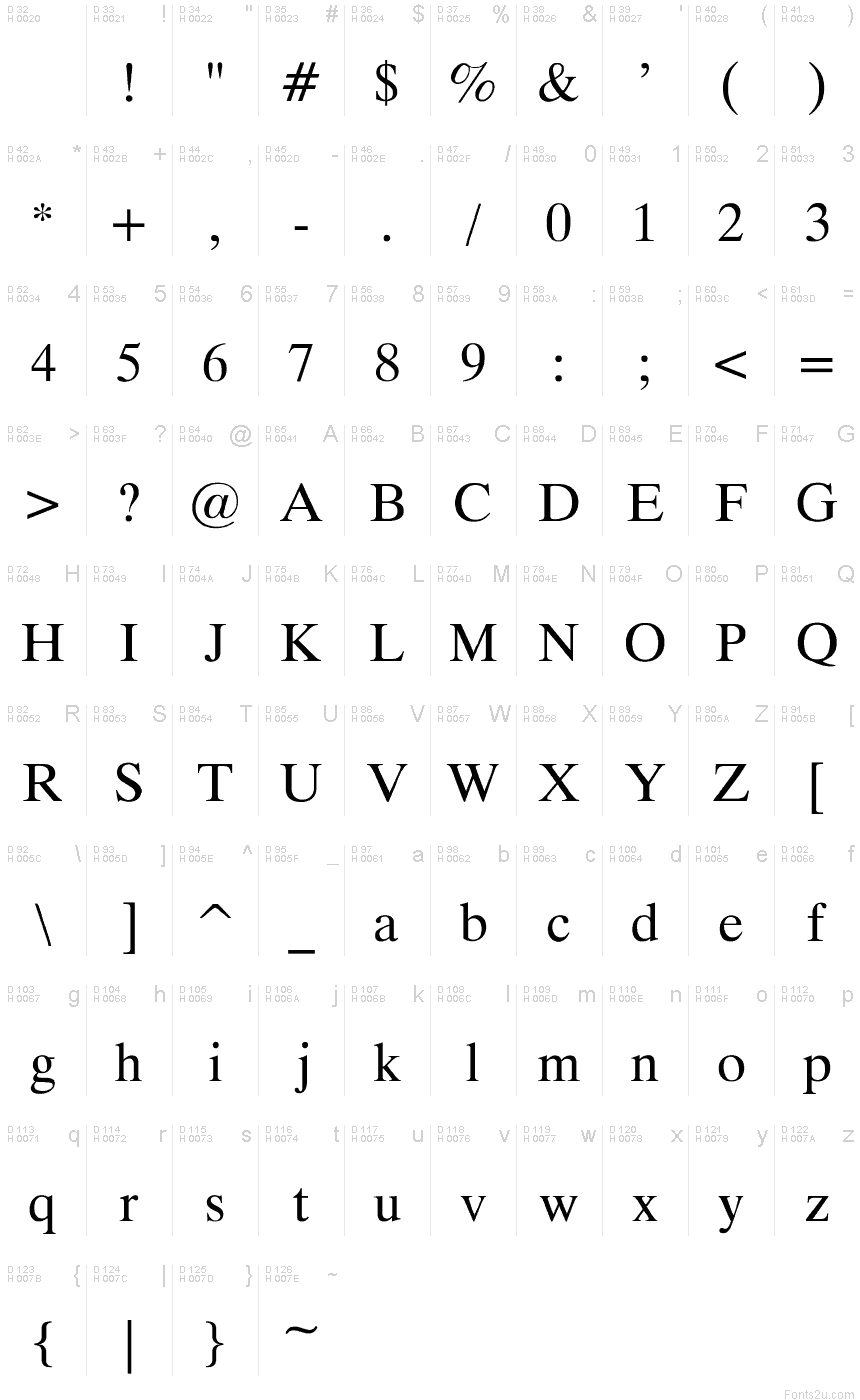
MicroTiempo od MicroCOM INC - Devoted to ShareWare to darmowy krój szeryfowy o wyważonym, książkowym charakterze typowym dla klasycznego druku. Jego rytm budują wysokie, lekko rozszerzające się kreski oraz ostre wykończenia szeryfowe, które nadają linii formalny wygląd, nie popadając przy tym w sztywność czy przesadną dekoracyjność.
Ta przemyślana faktura nadaje krótkim tytułom solidny charakter w nagłówkach redakcyjnych, na okładkach książek, certyfikatach, zaproszeniach oraz materiałach na wydarzenia kulturalne. Krój sprawdza się także w sygnetach marek i opakowaniach, gdzie stonowany kontrast i literacki charakter nadają nazwom większej powagi niż w przypadku neutralnych krojów szeryfowych.